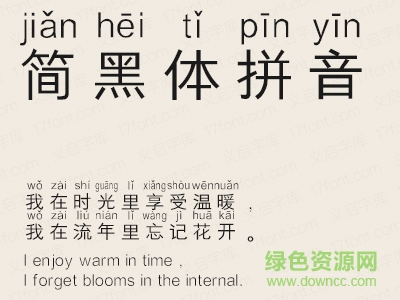
義啟簡(jiǎn)黑體拼音版是一款義啟出品的簡(jiǎn)體拼音字體,非常簡(jiǎn)潔實(shí)用,美術(shù)設(shè)計(jì)、文字排版等方面都可以使用,小編為大家?guī)?lái)免費(fèi)下載地址,歡迎大家來(lái)綠色資源網(wǎng)下載使用!
義啟簡(jiǎn)黑體拼音版,加了拼音的簡(jiǎn)黑體,媽媽再也不用擔(dān)心寶寶看見(jiàn)字不認(rèn)識(shí)了。